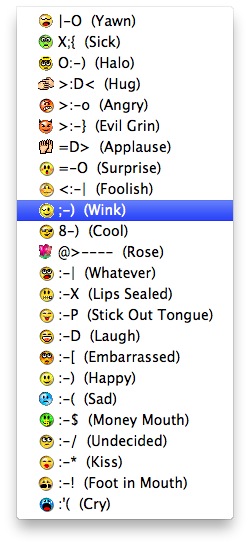
Notez que le bloc « Miscelleanous Symbols » (voir ici par exemple) d'Unicode comporte un certain nombre de smileys (code 2639, 263a, 263b, etc.) disponible ou non dans selon les fontes. Vous aurez alors l'avantage d'utilisez des symboles qui sont (dans l'idéal) adaptés à la fonte courante et vectoriels.
J'en ai trouvé des pages et des pages sur Internet. Je devrais y arriver.
Apparemment, c'est une pratique appréciée des auteurs japonais.
Dans un roman contemporain que j'ai à préparer, l'auteur utilise diverses émoticônes. Quelqu'un sait-il comment les intégrer dans le texte ? Faut-il une police particulière, et sinon où les trouver dans les polices standard ?
Au départ, ce sont des combinaisons de caractères typo, et c'est justement leur intérêt.J'en reviendrais donc aux sources, ces combinaisons, traitées dans la police du « style » en cours d'usage au moment où ils apparaissent. Maintenant, auteur ou éditeur penche peut-être vers du moins sobreŠ
Restons typo oh oh !